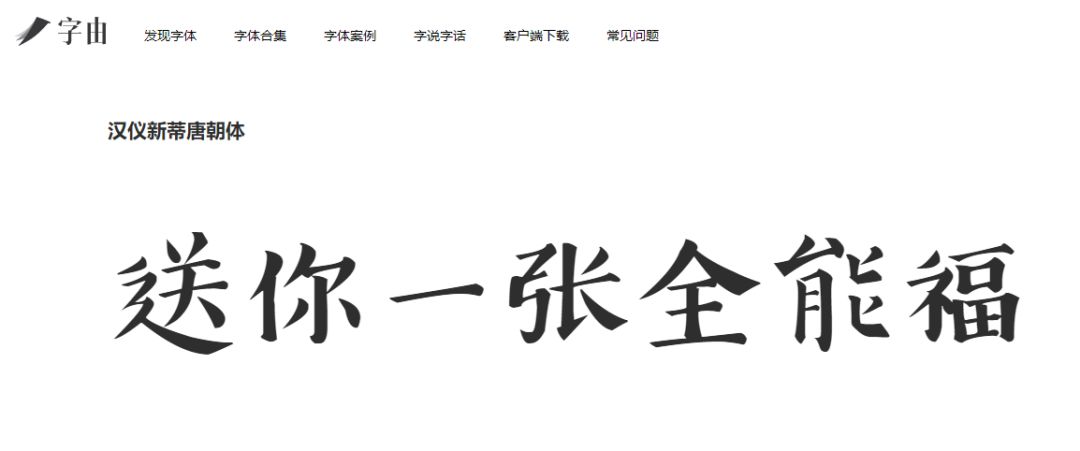
别加好友了,设计师都是这么集五福的~
自集五福以来,全民的扫一扫,浇一浇,答一答就停不下来,哦对了,还有一个换一换~
可柚子就喜欢难为自己,那么早集齐了没意思。
不过也别连着好几天全是和谐福,友善福啊,难道我看起来那么人畜无害嘛?
那就给我一张花花卡啊(伦家长得多像祖国的花朵),结果马云爸爸,真就写了一个开挂的福,据说有田有猪有网有支付宝。
咦,“支”在哪,看下篆体字:
这个彩蛋藏得很深啊,难怪一扫必出沾福气卡,不过是一次性的,如果不能复制到需要的,依然……瞎耽误功夫。
没有就继续,反正我就跟敬业福、花花卡死磕到底了,还能顺便看看插画~
谁叫它用的是汉仪新蒂唐朝体呢,字由的出现,就是这么猝不及防~
前面说的都不重要,下面才是重点,毕竟春节前没那么多时间,要加班到浮肿肿肿……
也不可能去度娘,那样还不如给我来一刀,特别是眼睛。
那怎么办?有人发明了自己动手,五福到手~
但这个概率太小,你以为你是马云啊!
去字体网站多方便,可以随意搜想要的福~
而且,可以根据五福的字型特点找。
比如爱国福,是典型的书法体,爱得很豪放!
而富强福呢,又粗又圆润,一看就是腰杆子都挺起来了,不过我对它的定义是,让别人服了,你就强了,哈哈哈。
提起和谐,我就头大,已经有十多个了,真的不想被和谐了~那就试试下面的吧,一个方方正正,守规矩的福娃。
友善福是这里面唯一觉得不太合适的,应该萌萌哒,看起来才是好基友嘛?
最后一张敬业福,看起来就像设计师的头发,所以我给你整茂密了,祝你一片富饶~
好了,知道你想要花花,给你一张灵符,哈哈哈哈哈!
再说个知识点,知道为什么我们有过年写福字的习惯吗?
因为早在甲骨文时期,“福”字就作为一种象形文字出现了,代表装酒器具,在神前的形状,有“祈祷”、“纳福”之意。
虽然刚开始只有帝王才能享受,但周朝的“殷末三仁”箕子,首次提出了“五福”的说法:“一曰寿,二曰富,三曰康寧,四曰攸好德,五曰考终命”,才让“福”走进了平常百姓。
现在的福字,“示”由右移到左,而“畐”由左移到右,所谓:“福,祐也。从示畐声。方六切。”
知道了吗?还有几天,快去集福吧!